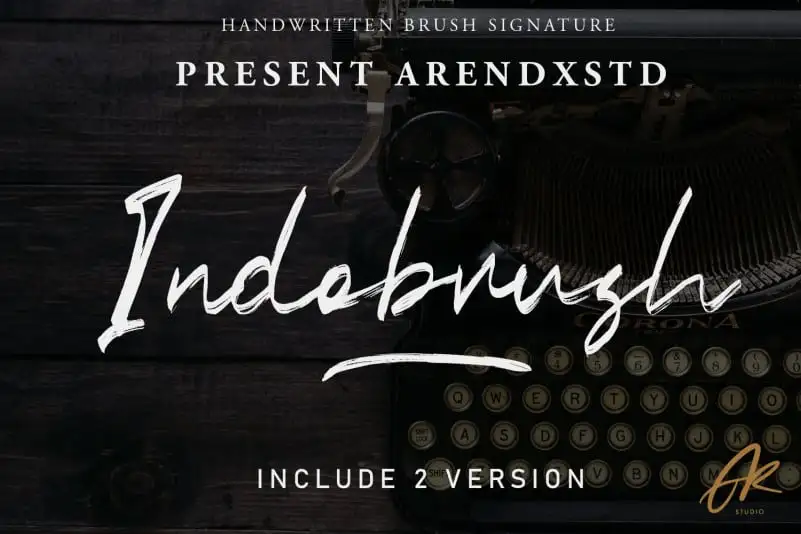
A Indobrush Brush Font é uma elegante escolha para designers que buscam dar uma cara única a suas criações digitais. Esta script font foi desenvolvida pelo designer brasileiro Arendxstudio e carrega consigo um estilo dinâmico e vibrante, ideal para várias necessidades de projetos gráficos. Seja criando logomarcas, cartões de visita, embalagens ou até mesmo publicações nas redes sociais, a Indobrush Brush captura o toque pessoal necessário para dar vida aos seus trabalhos. Com uma paleta vibrante e um touch naturalmente autêntico das canetas do usuário, esta fonte é perfeita para projetos que exigem um apelo humano e artesanal. Não importa qual projeto você está tentando atingir com a Indobrush Brush: seja ele branding, design de marca ou mesmo elementos como imagens fotográficas ou até mesmo marcas digitais — ela o ajudará a alcançar o resultado desejado.